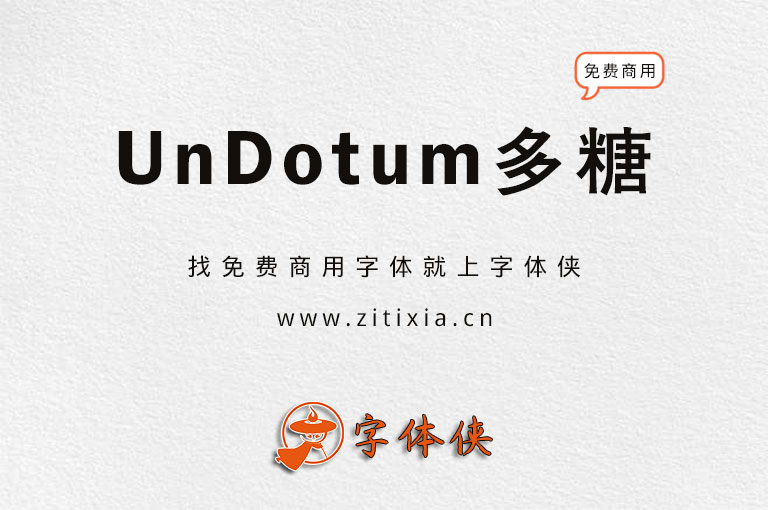
UnDotum多糖体_无版权黑体字体下载
UnDotum多糖:韩国Un系列开源字体 不一样的韩系汉语文字。UnDotum是韩国Un开源系列字体中的其中一款,因为是韩国字体,为了方便中国大陆的小伙伴容易记忆,我们给其起了个中文名“多糖”,实际上并没有对字体文件做任何修改,这款字体在PS中的名字依然是“은 돋움”。
韩国Un系列字体包括核心系列9款字体和额外系列10款字体,我们将会在稍后的时间逐一进行更新。不过较为可惜的是,这系列字体都是以繁体为主,支持简体的字数较少,中国大陆的小伙伴若要使用这套字体会比较难受。
韩国Un系列字体是由@Koaunghi Un于1998年以HLaTeX type1制作而成,作者在20世纪90年代末制作type1字体用于韩国的Tex(JLaTex[1]),并以GNU GPL授权许可进行发布。于2003年,由@Won-kyu Park使用FontForge(PfaEdit)转换成ttf文件进行发布。